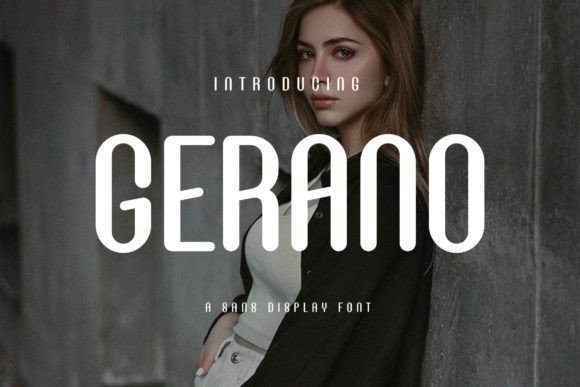
Gerano
Het vinden van de juiste ontwerpelementen kan lastig zijn, maar Gerano biedt een uitzonderlijke collectie die uw werk direct naar een hoger niveau tilt.
Of u nu POD-producten (Print on Demand), huwelijksuitnodigingen of afbeeldingen voor sociale media maakt, Gerano is een ideale keuze.